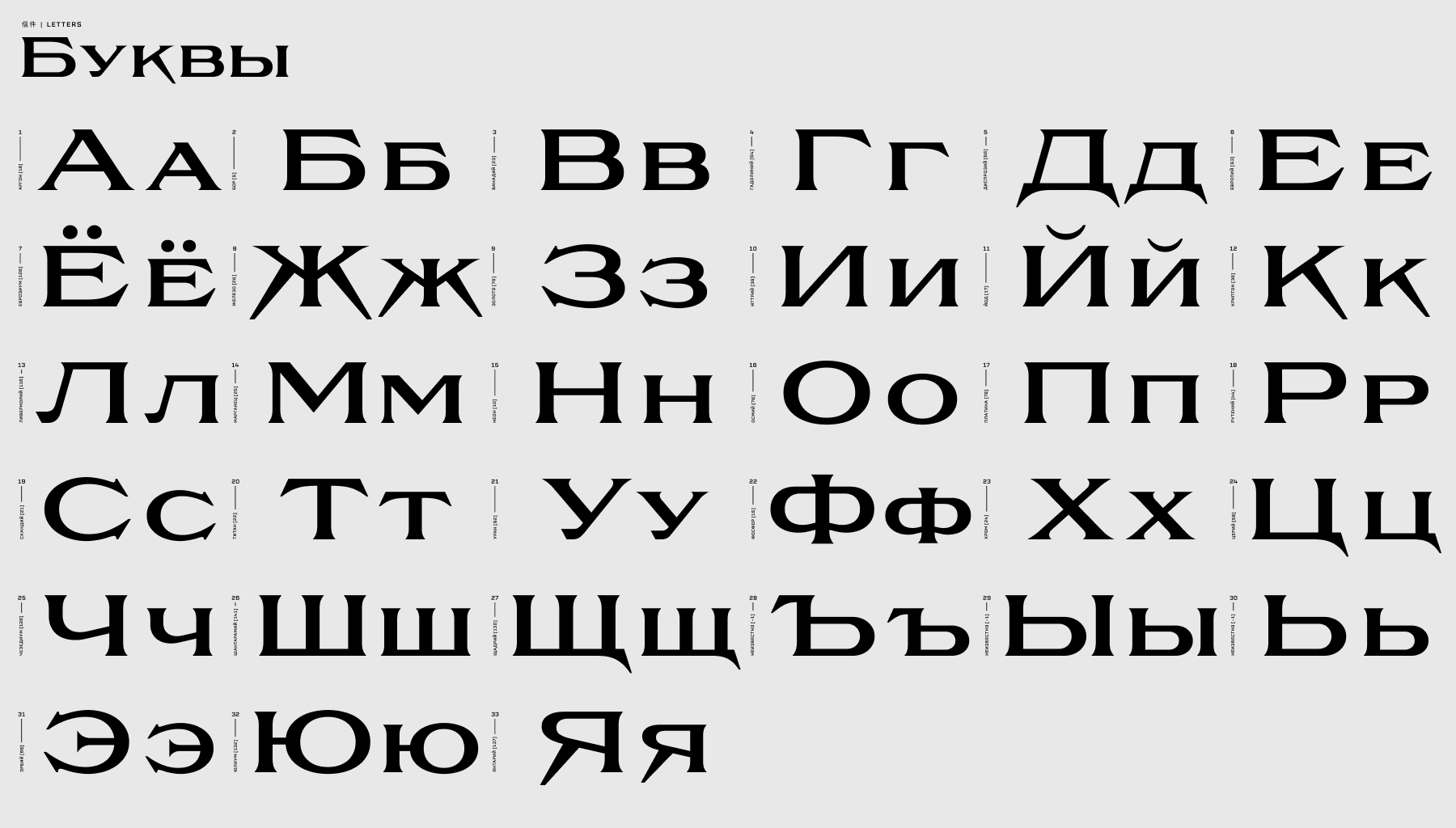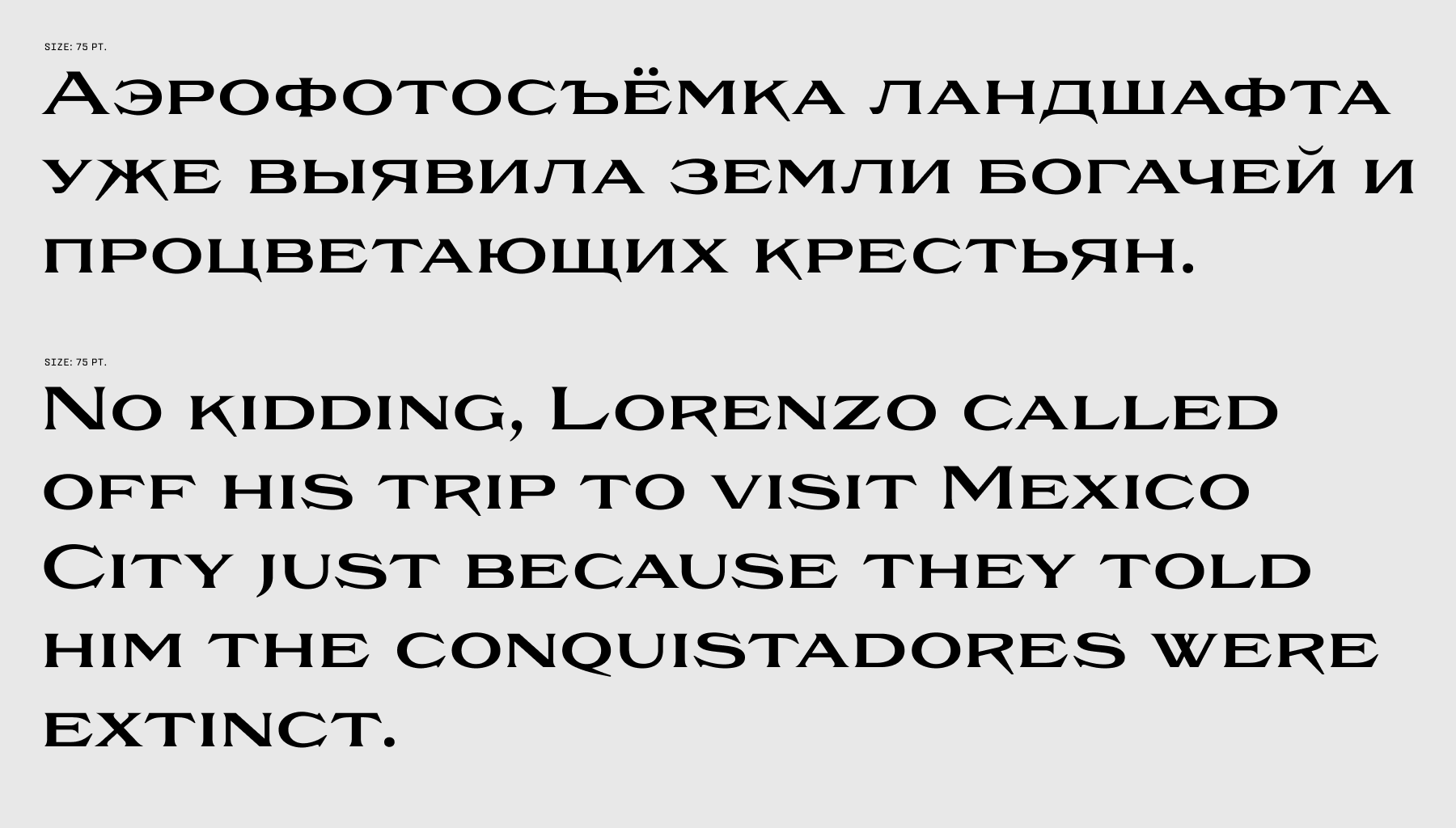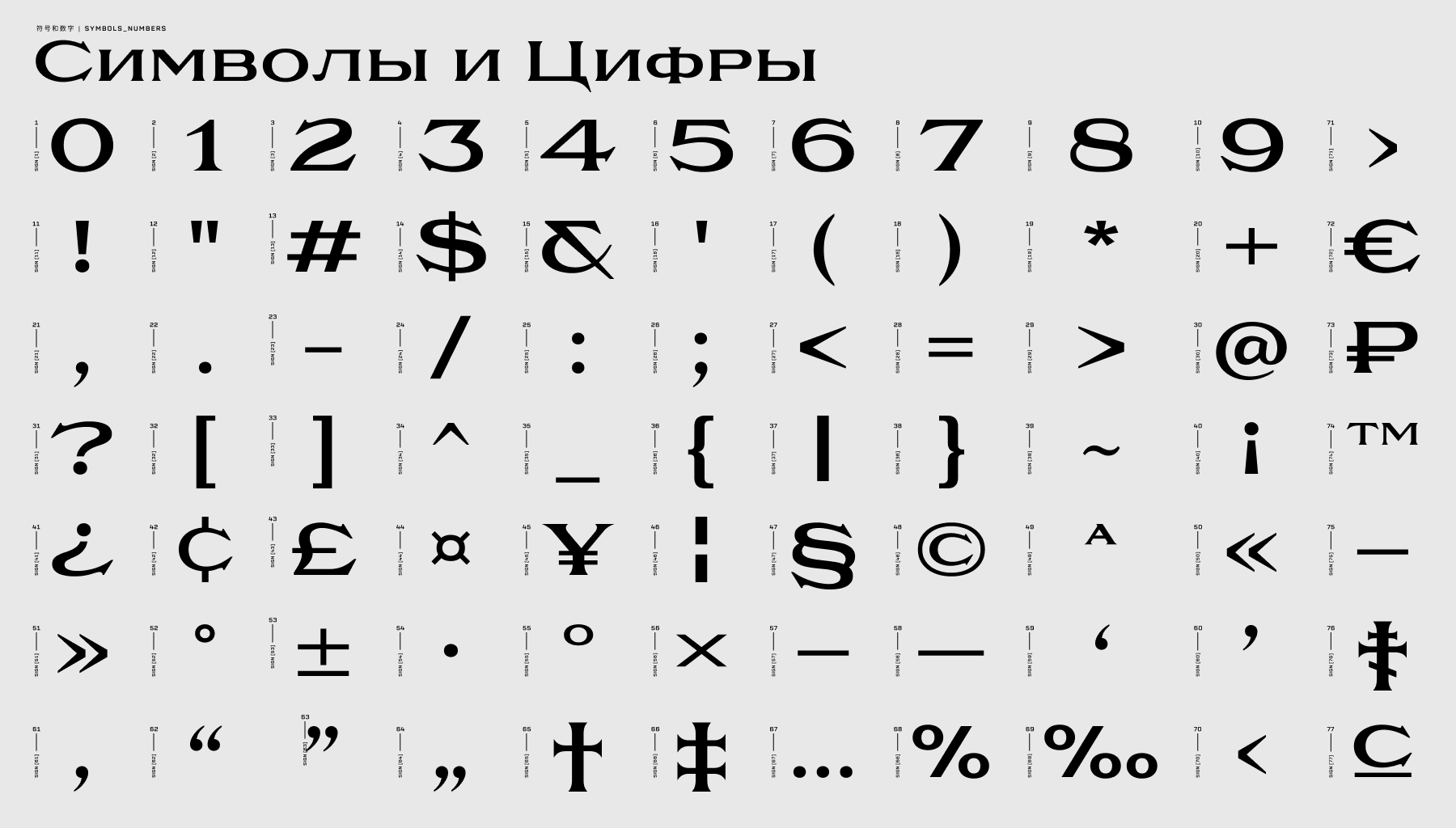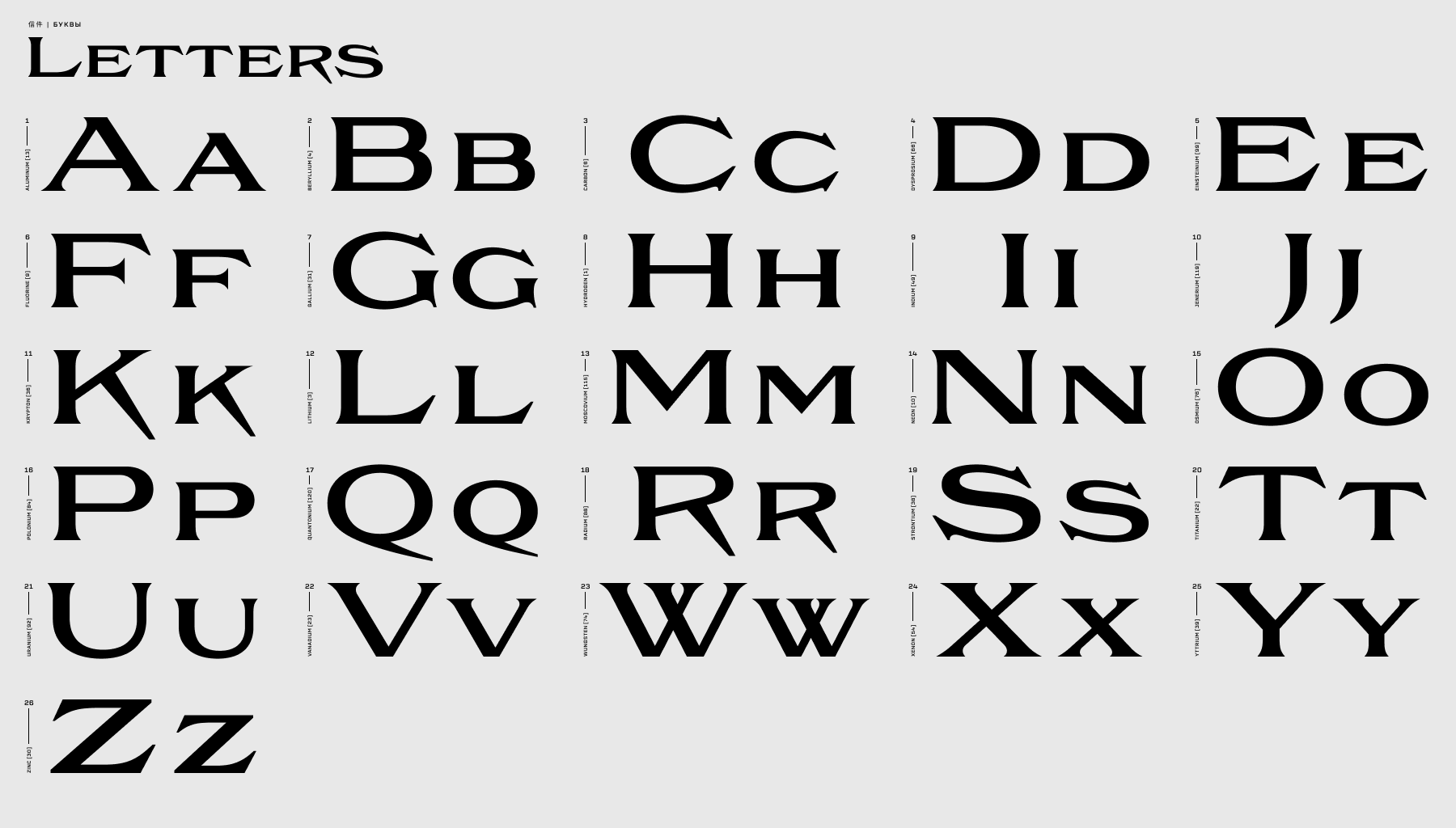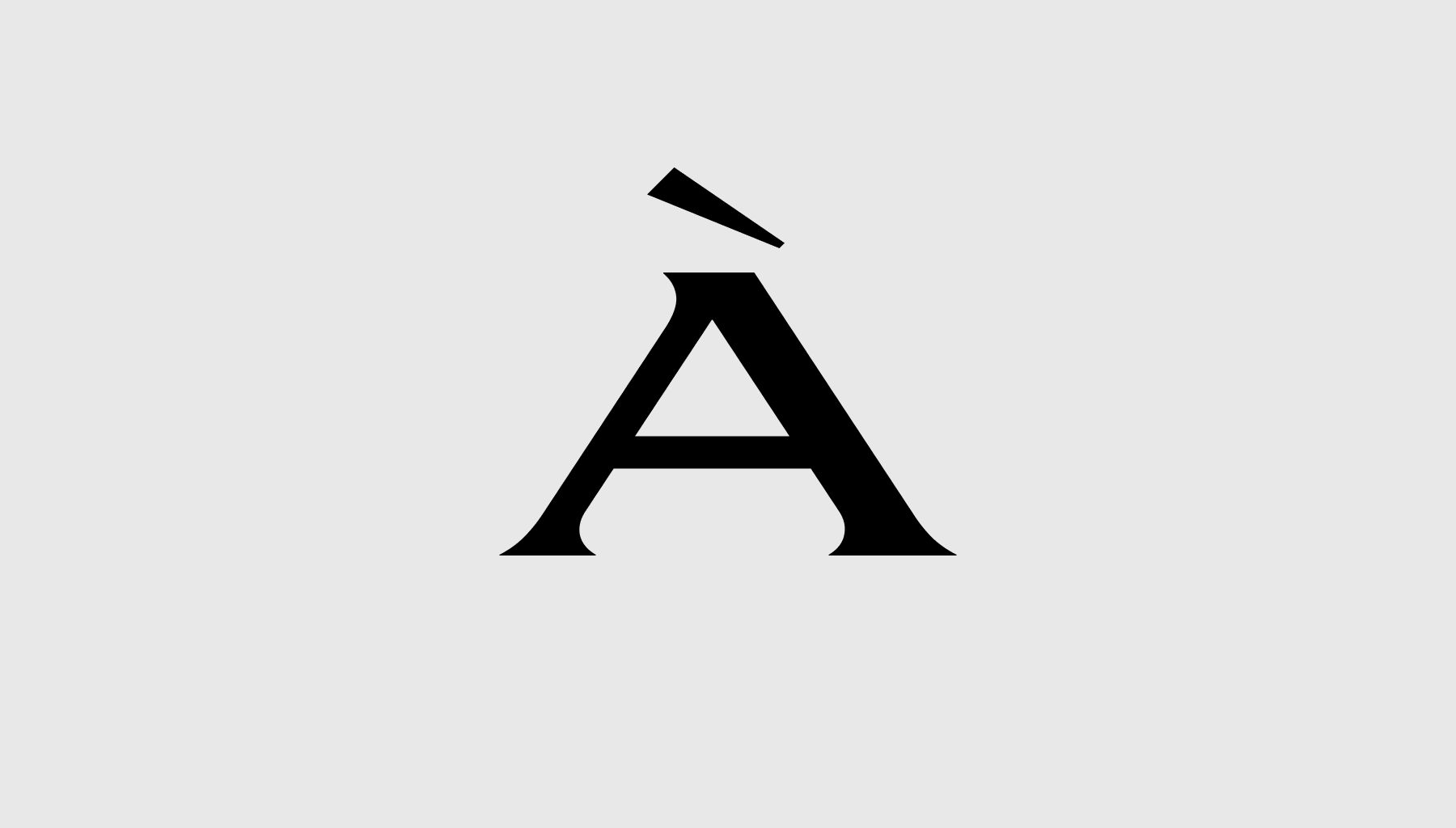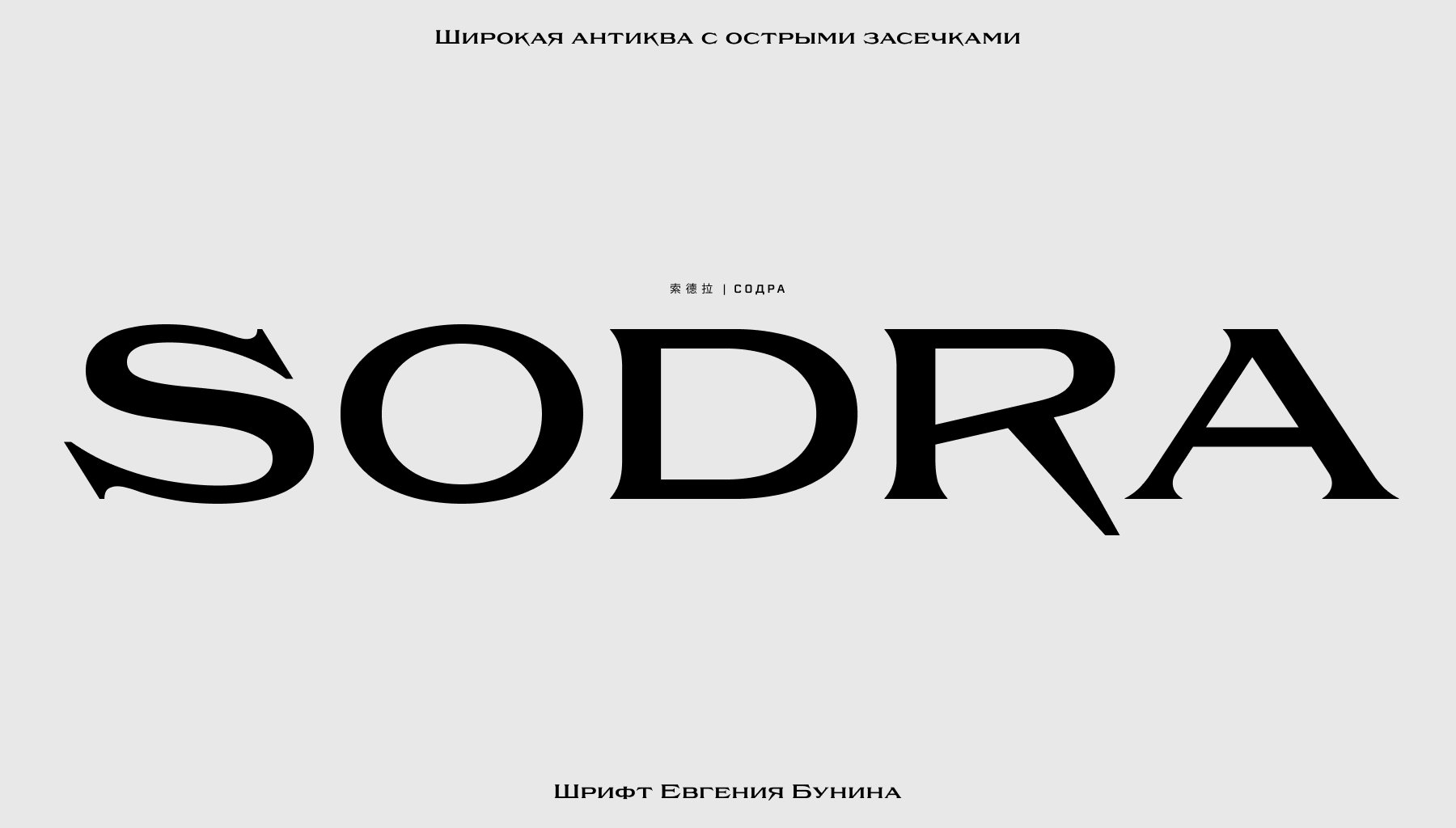
Шрифт Sodra
Sodra - это широкая акцидентная антиква с острыми засечками. Этот шрифт появился из отрывка манифеста “Manifesto del Futurismo” автора Filippo Tommaso Marinetti. Одно короткое слово стало вдохновением и напутствием для создания данного шрифта. Попытка создать что-то уникальное и выделяющиеся из множества других антикв, попытка добавить в что-то историческое немного современного. Особая эстетика и его выразительность, которую передаёт шрифт, заставит всматриваться в каждую букву и привлекать внимание.
Шрифт разрабатывался долгое время и над ним проведена кропотливая робота. Большая языковая поддержка, почти 500 символов и больше 2000 кернинг пар. Хинтинг(мои первые попытки) и тестирование самого шрифта в деле и в самых разных способах применения.
Применение шрифта очень широко. Будь то логотип или мерч, заголовок или продуктовый дизайн. Характер шрифта не ограничивается чем-то грубым и мрачным, наоборот, всё зависит от того, как вы на него посмотрите.
Евгений Бунин
Евгений Бунин, Шрифтовой дизайнер